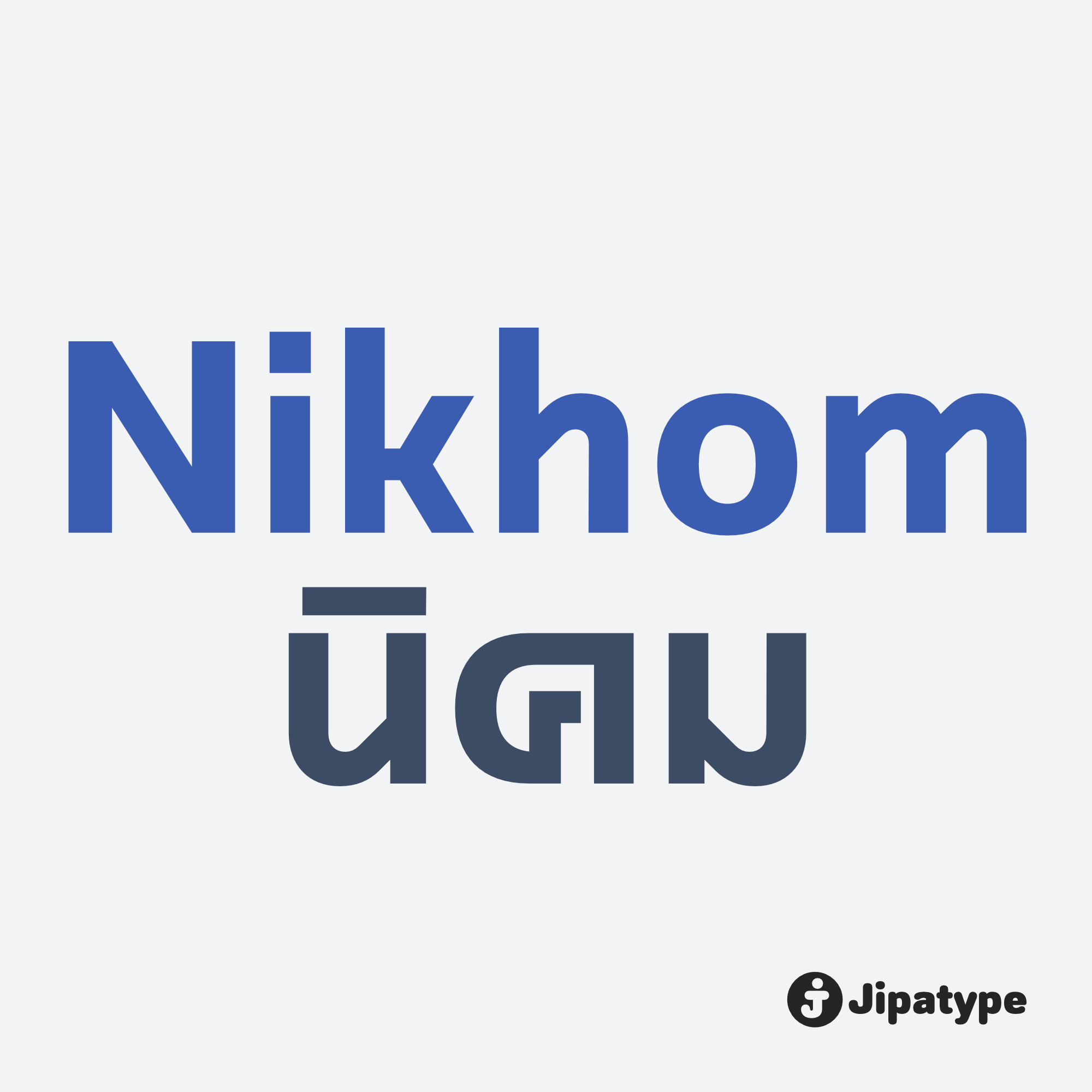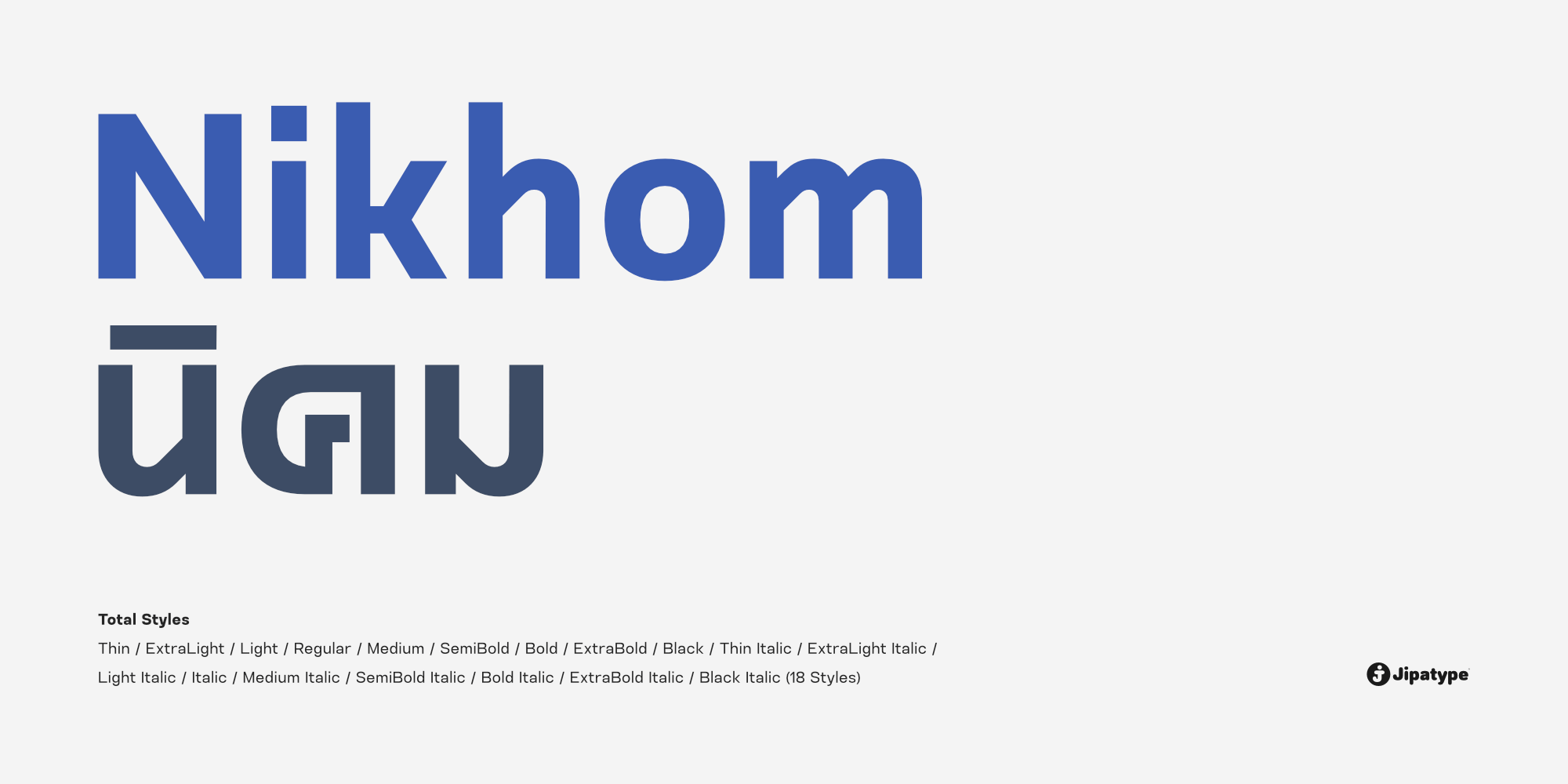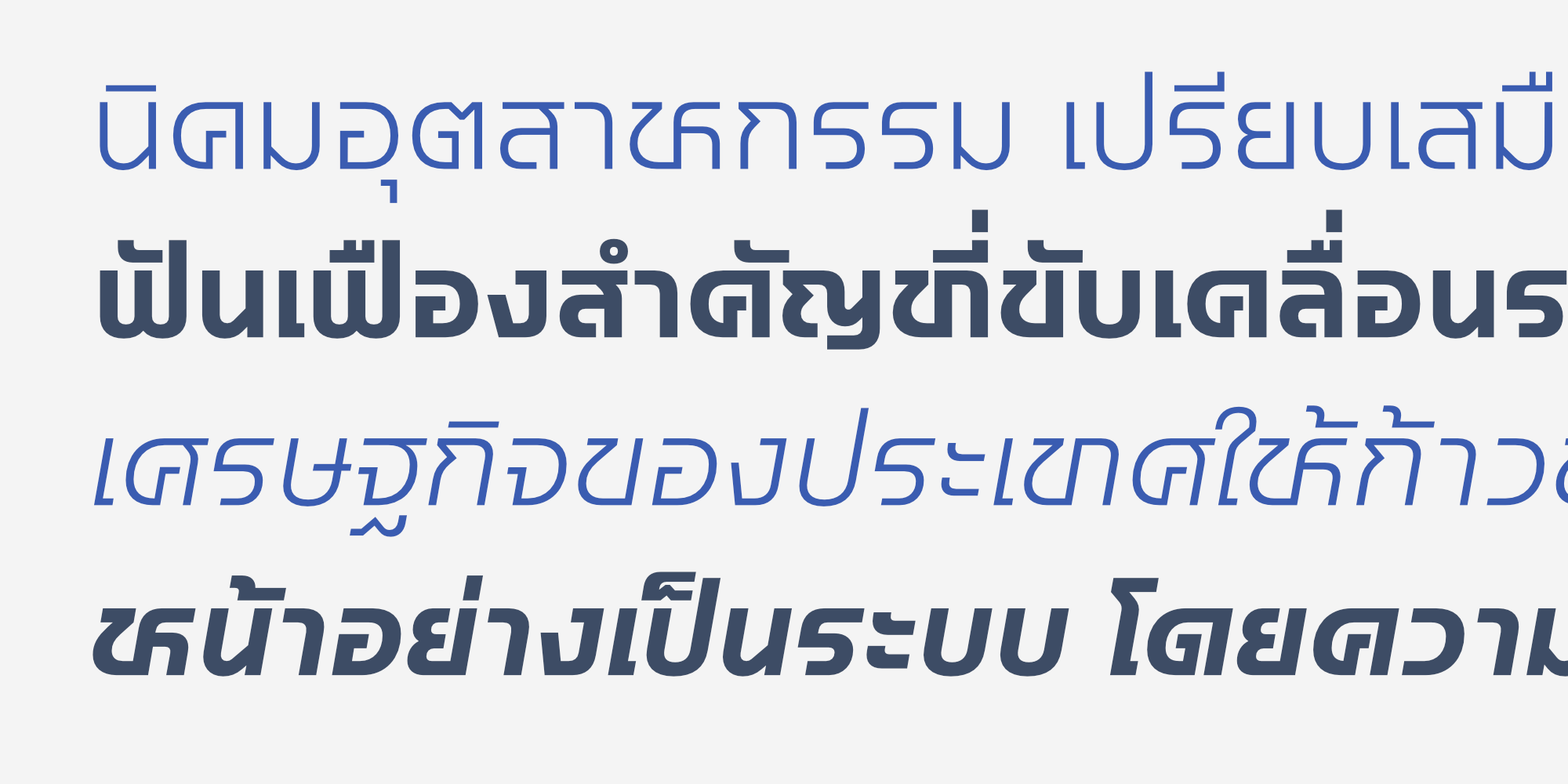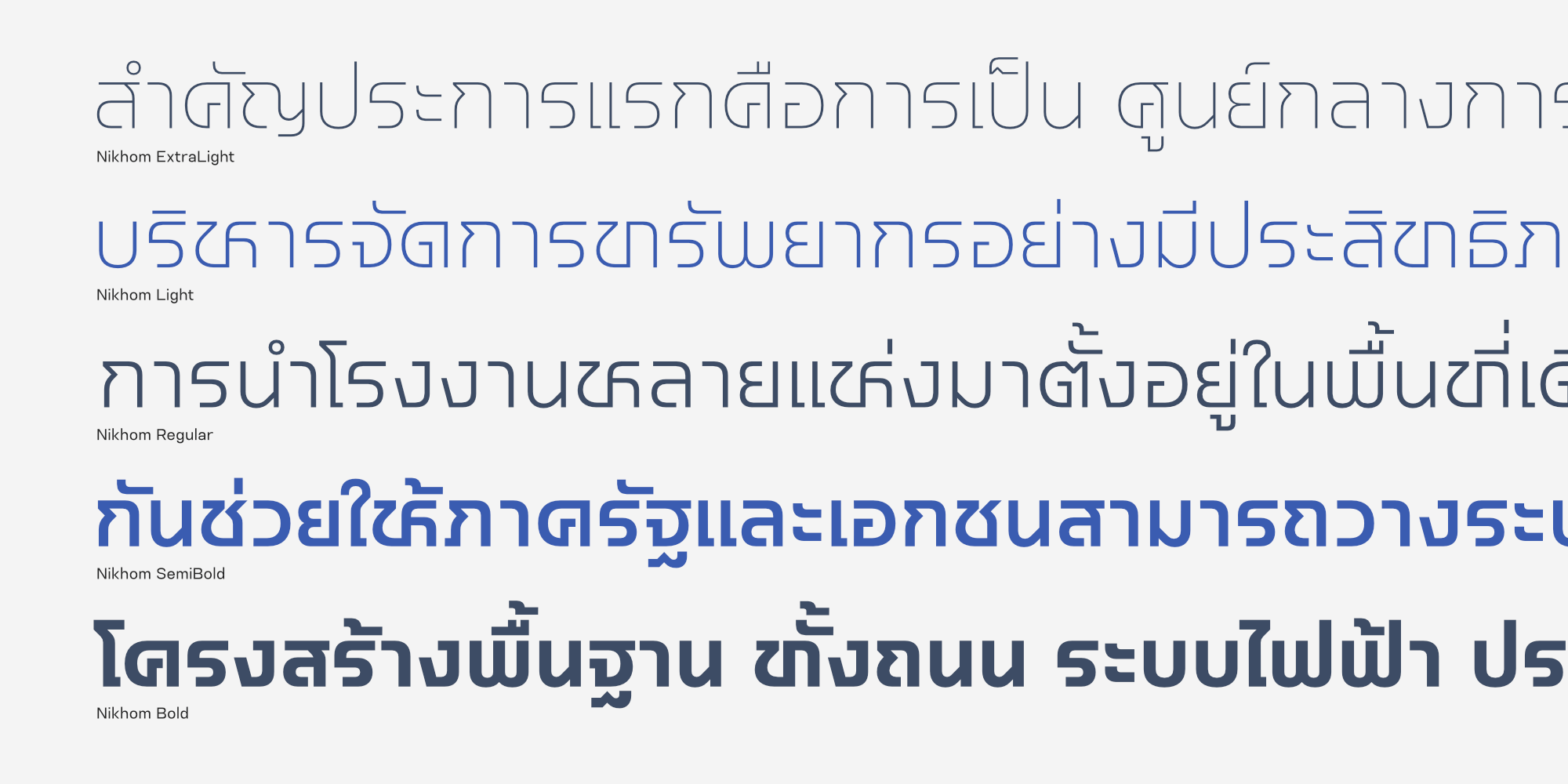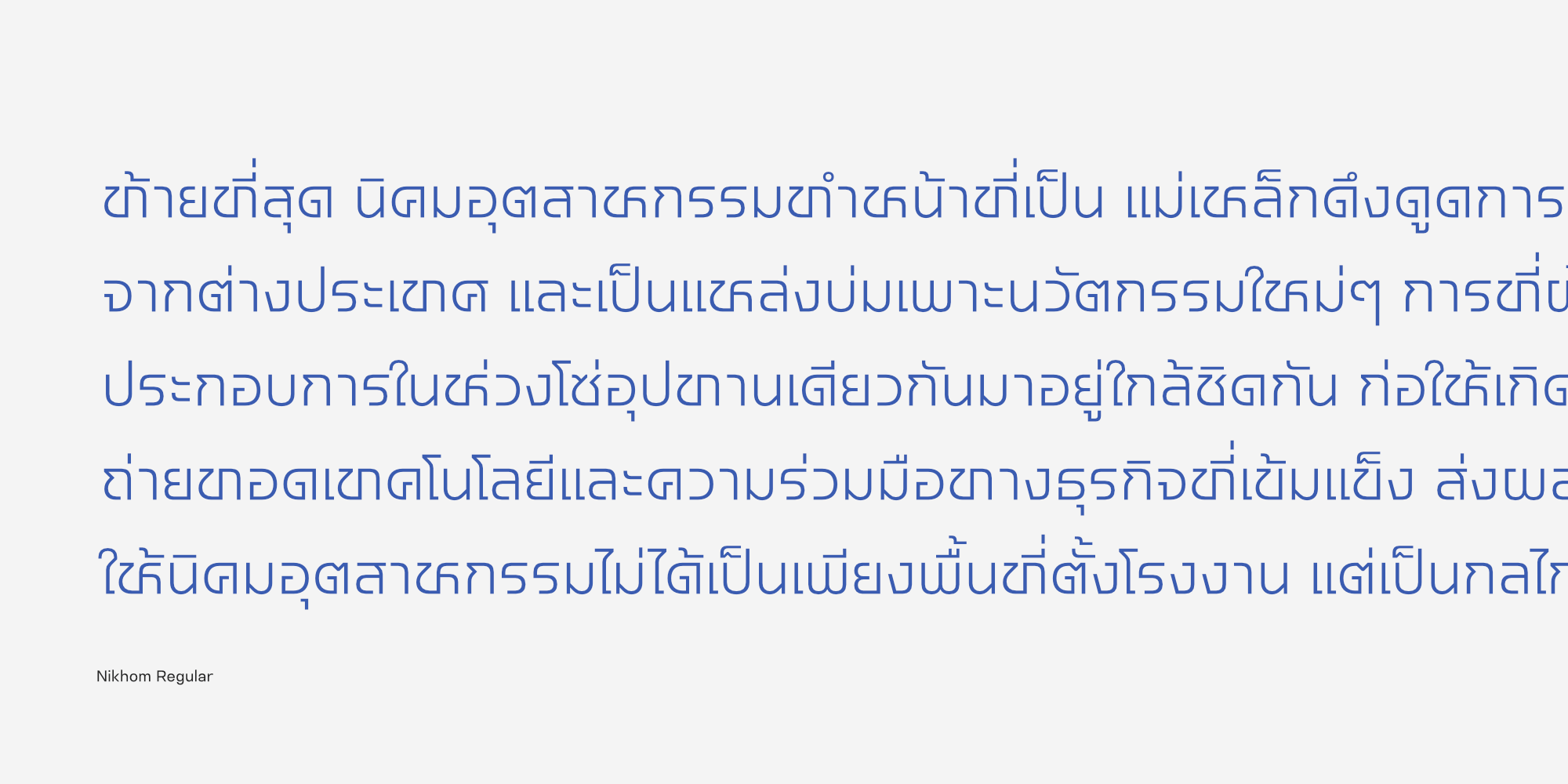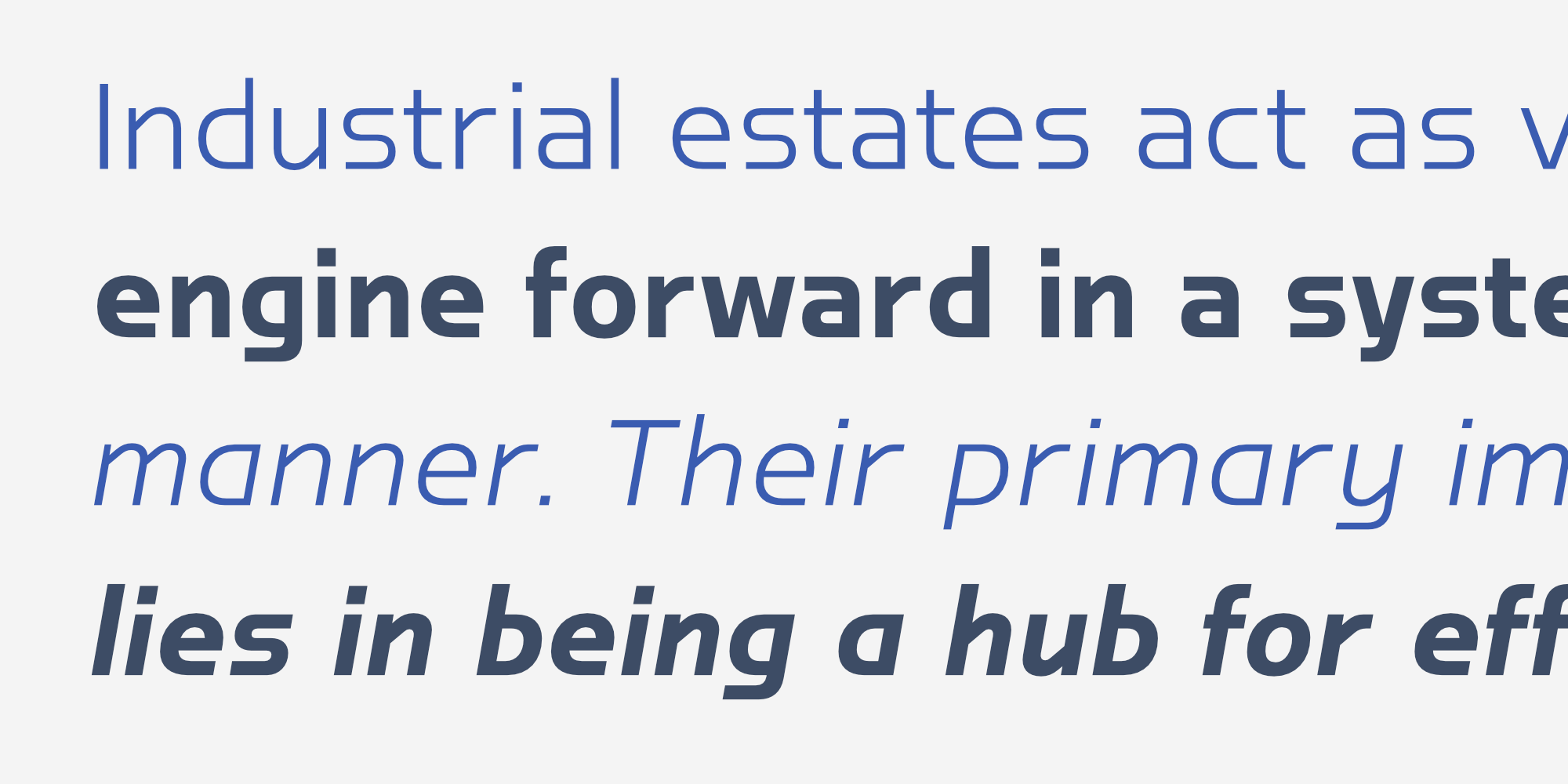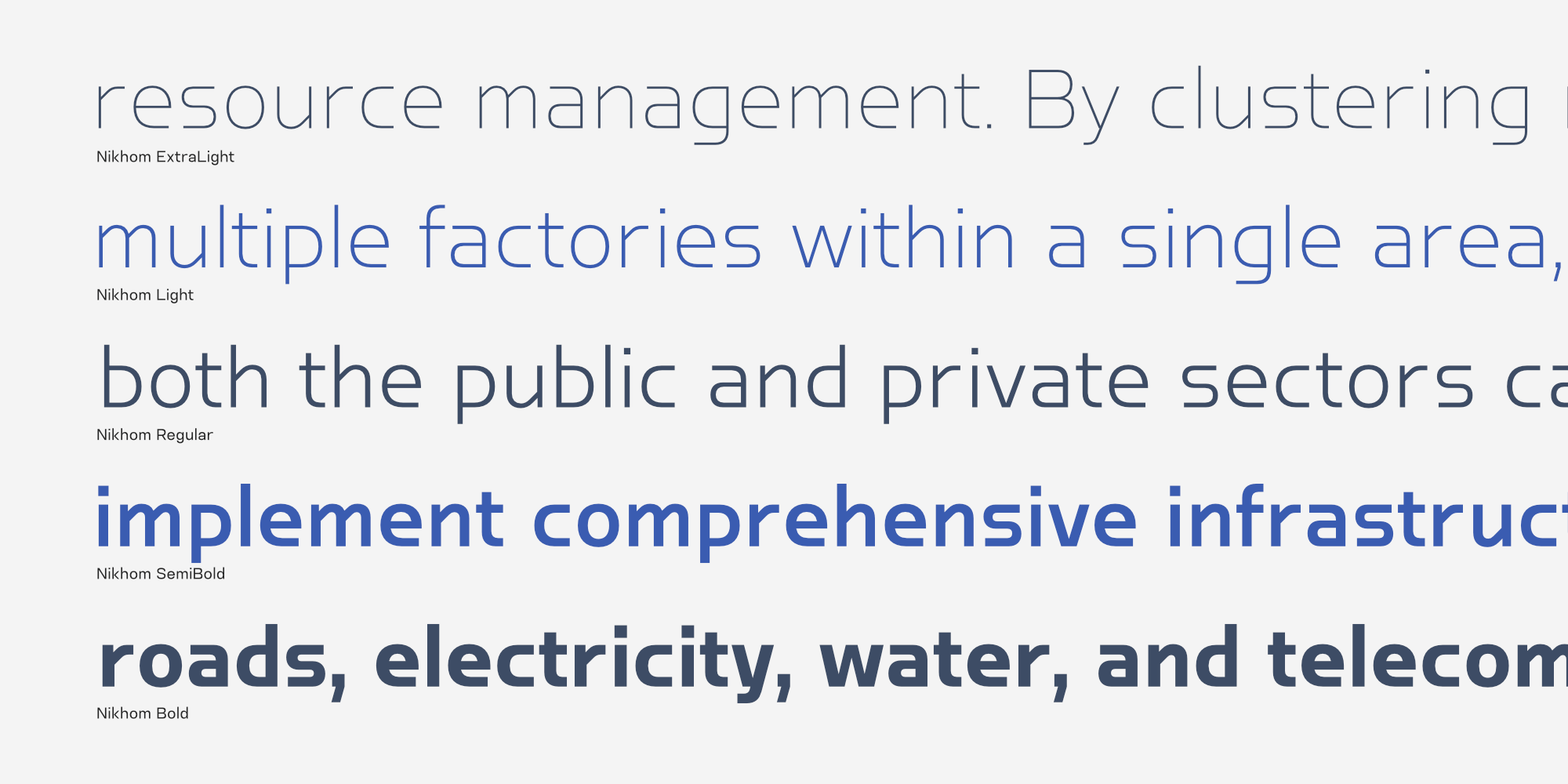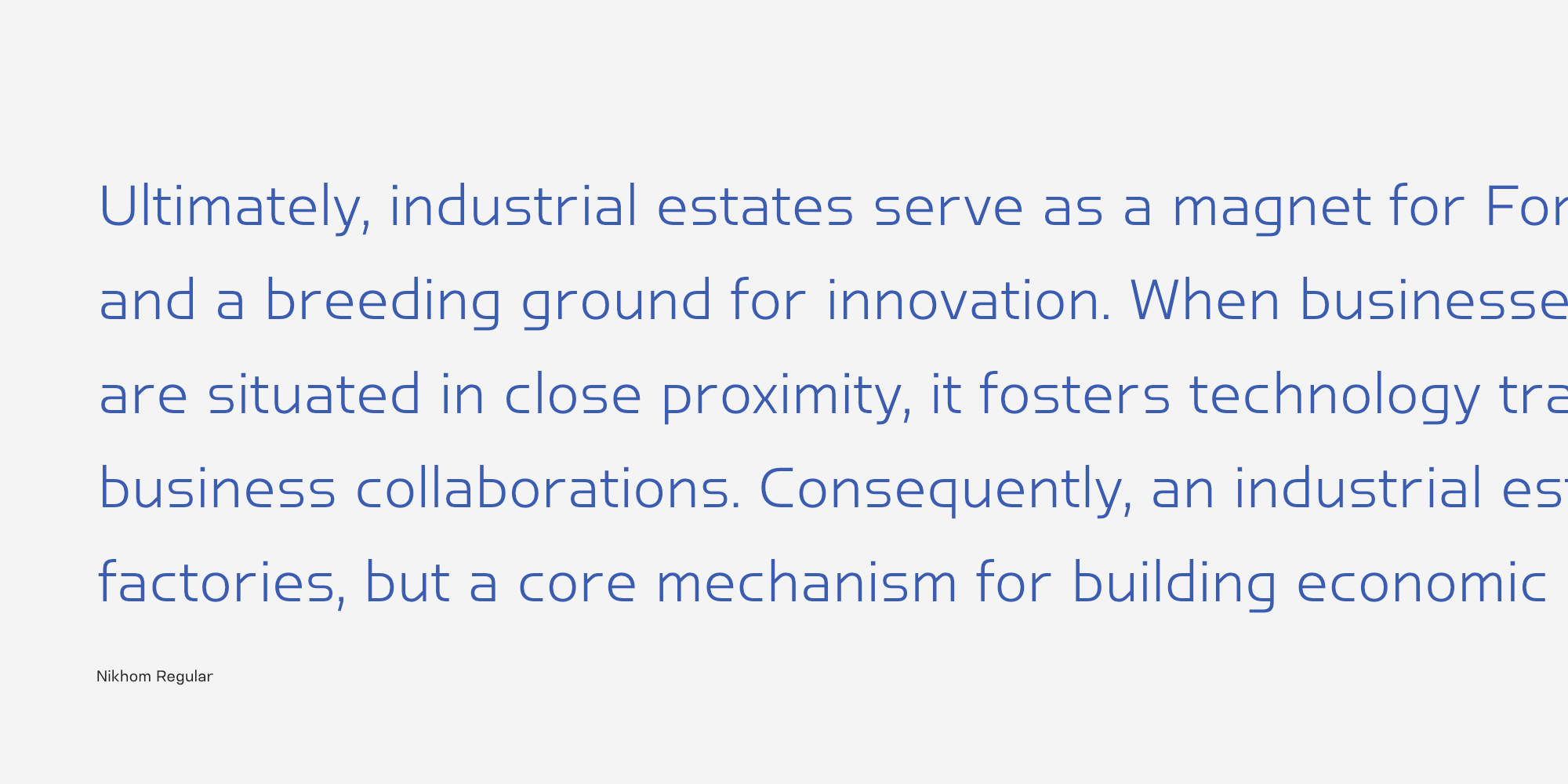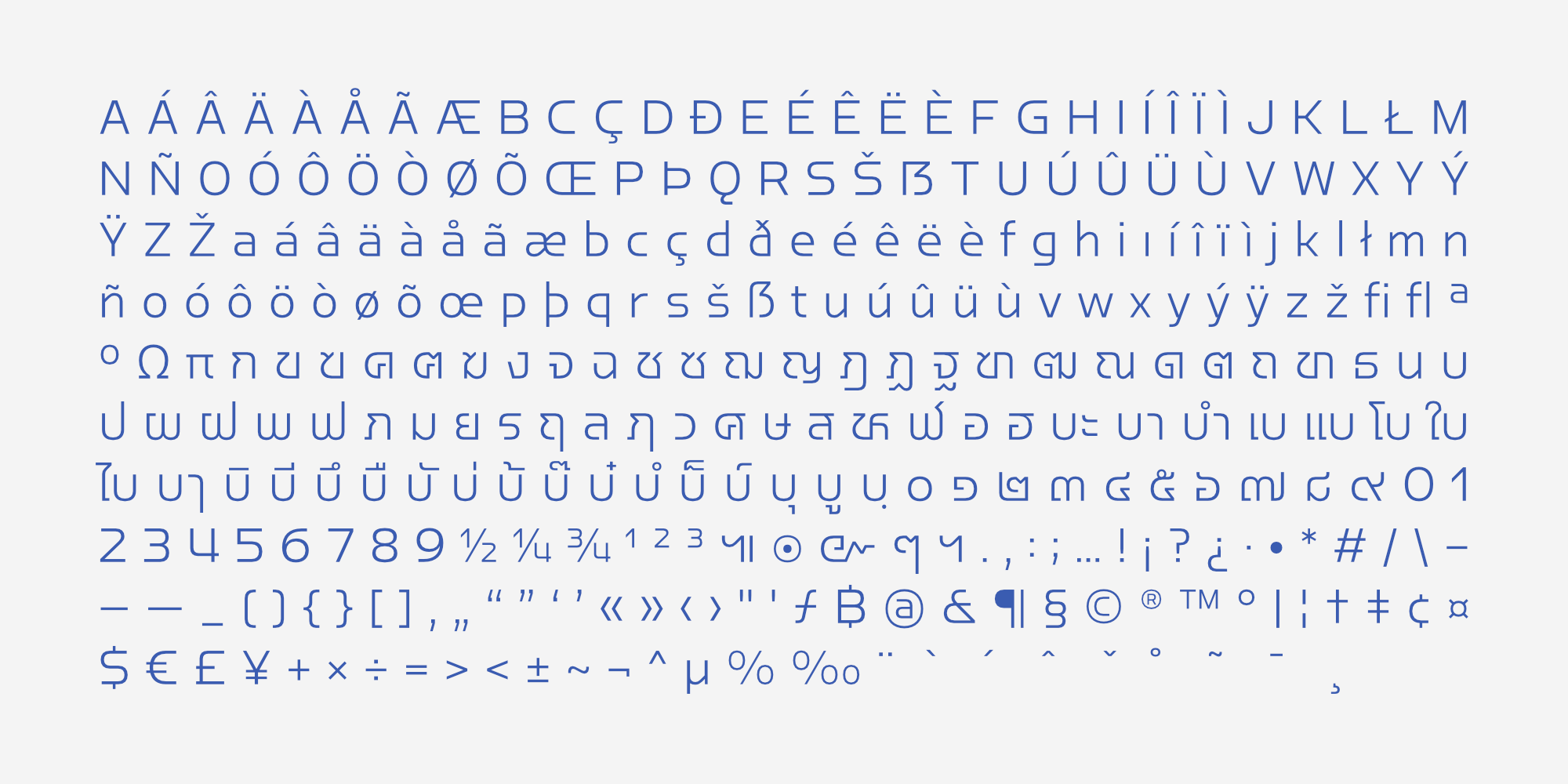
นิคม | Nikhom
Nikhom เป็นชุดแบบอักษร Sans Serif ที่เน้นความเรียบง่ายและดูสะอาดตา มีจุดเด่นอยู่ที่การออกแบบรูปทรงตัวอักษรให้มีความแบนราบทั้งส่วนยอดและส่วนฐาน เพื่อให้เส้นสายดูขนานไปกับเส้นฐาน (Baseline) และเส้น x-height โครงสร้างนี้ช่วยให้ภาพรวมของข้อความดูเป็นระเบียบ มั่นคง และสบายตา
โดยรองรับทั้งภาษาไทยแบบไม่มีหัวและอักษรละตินที่มีลักษณะเป็นเรขาคณิตเข้าคู่กัน จึงเหมาะสำหรับสื่อประชาสัมพันธ์ที่ต้องการสื่อสารถึง ความมั่นคงแข็งแรง ความน่าเชื่อถือ ความทันสมัย เช่น ภาคส่วนอุตสาหกรรมการผลิตต่างๆ
ออกแบบโดย : อานุภาพ ใจชำนาญ (Anupap Jaichumnan)